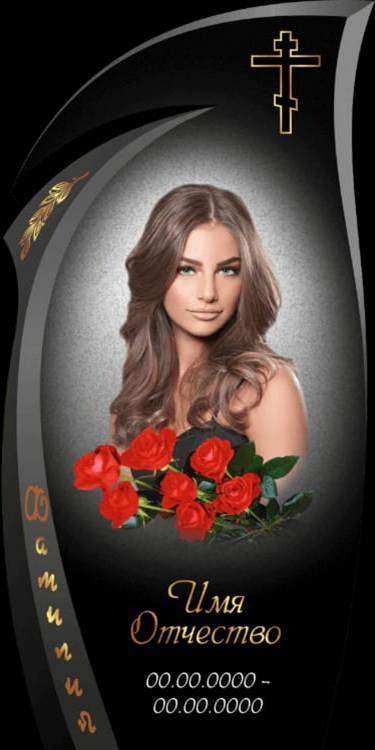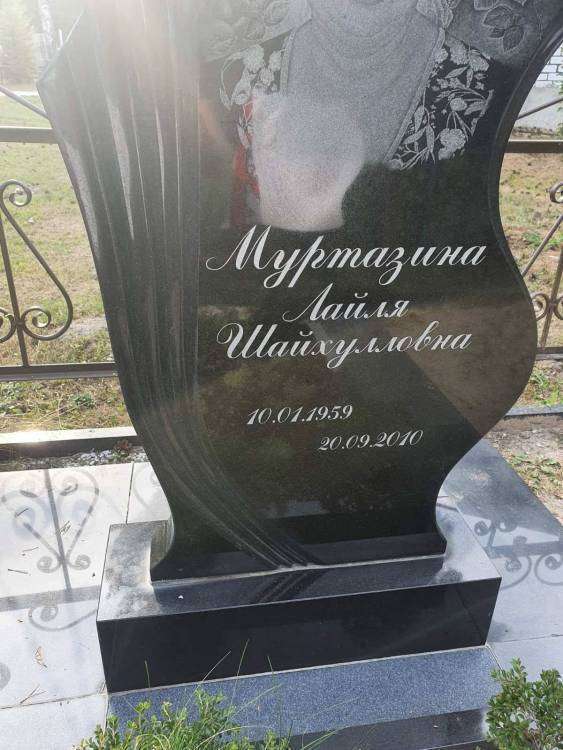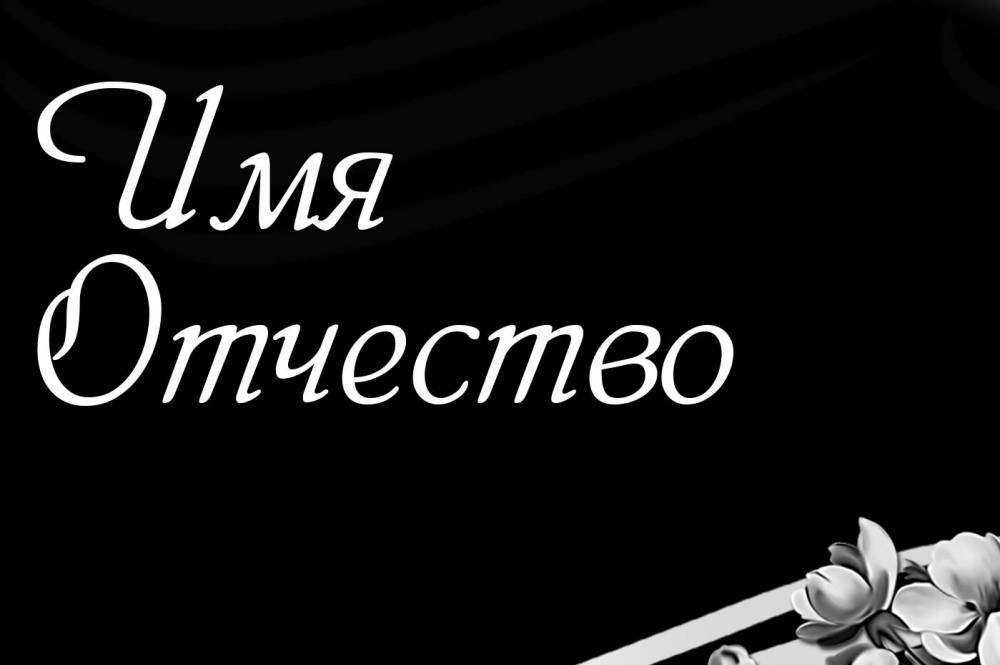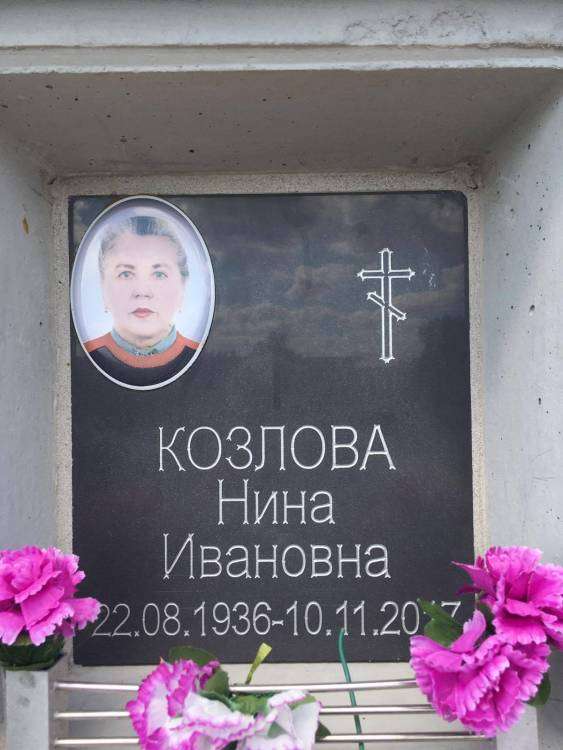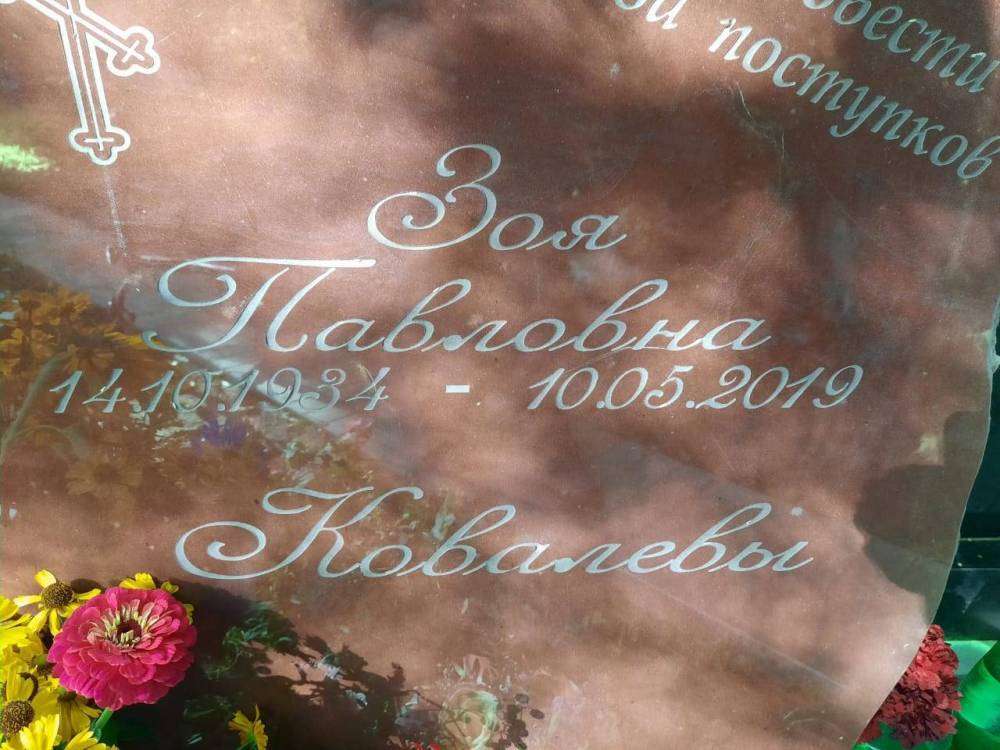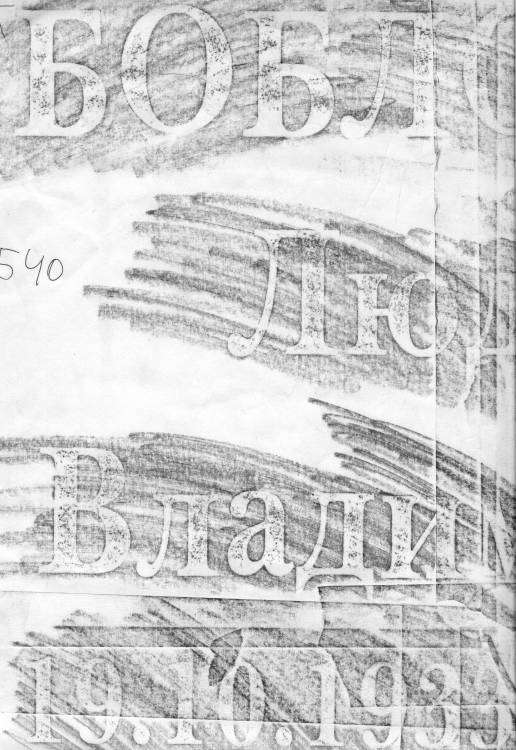
Ludvig van Bethoveen
:neeet: строчные буквы низкие слишком. "в"  совсем не похожа
@minus да , конечно, это на случай полного безрыбья, что то из этого смудрить при желании и не более...
подскажите что за шрифт?
Ну дык Calligraph же. Мне так кажется))@Aidar606
но все палочки соединили )
Phyllis Regular
кириллицы нет :laie_48:
Ищу русский вариант этого филипса
minus,    PhillippScript  вот русский вариант
Может кто встречал. Цифры  интересные. Обратите внимание на тройки)
Он-он) только у тебя текст сжали по ширине или вытянули в высоту, по точкам даже видно :)
Всем привет, подскажите что за шрифт, ну уж очень требовательный заказчик
@Partas привет, попробуй Algerian Regular
помогите опознать.
@Яшa прям Diavolo EF Regular. Но русского что-то нет